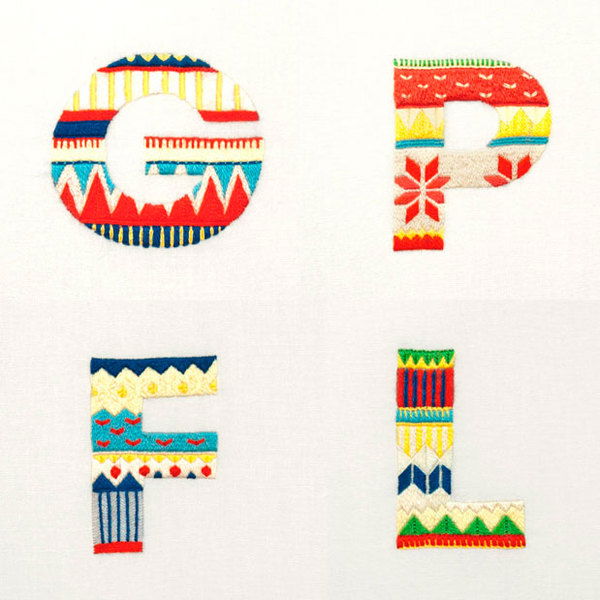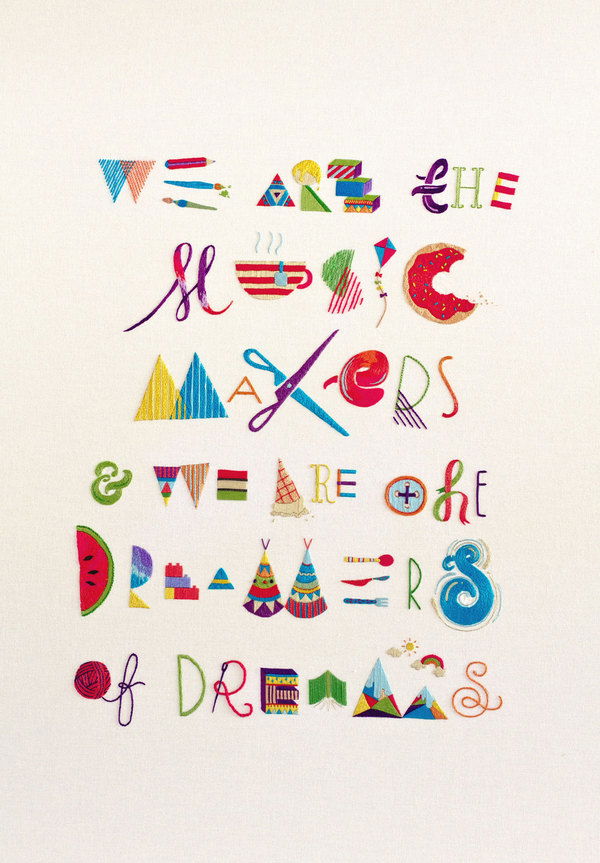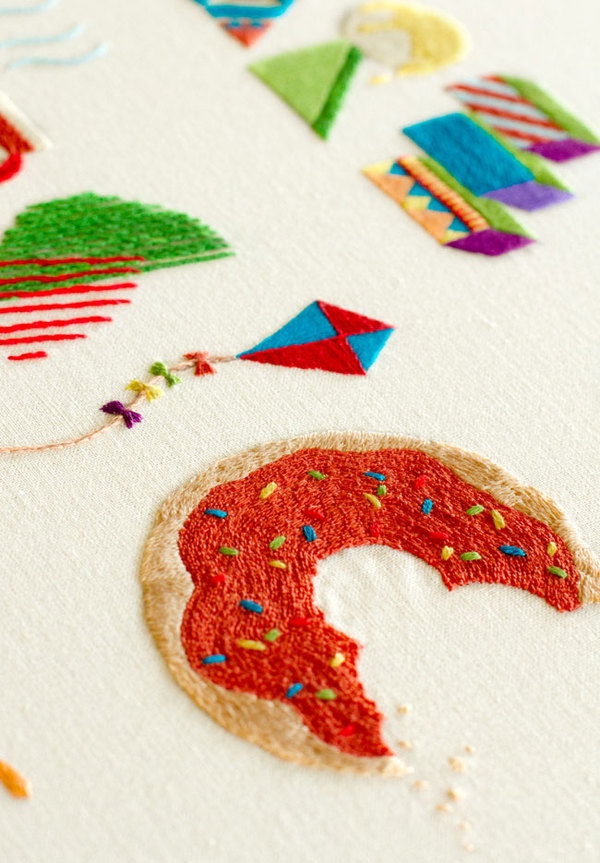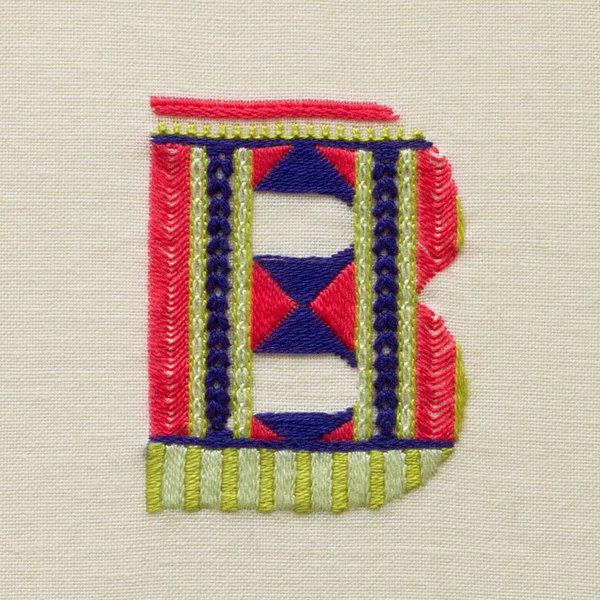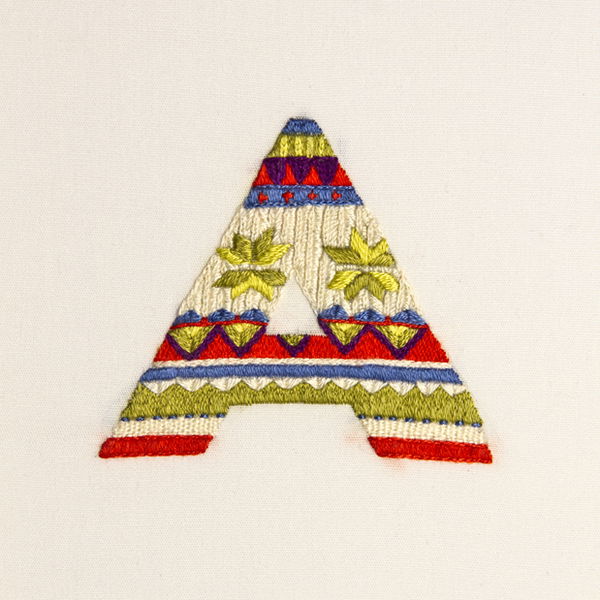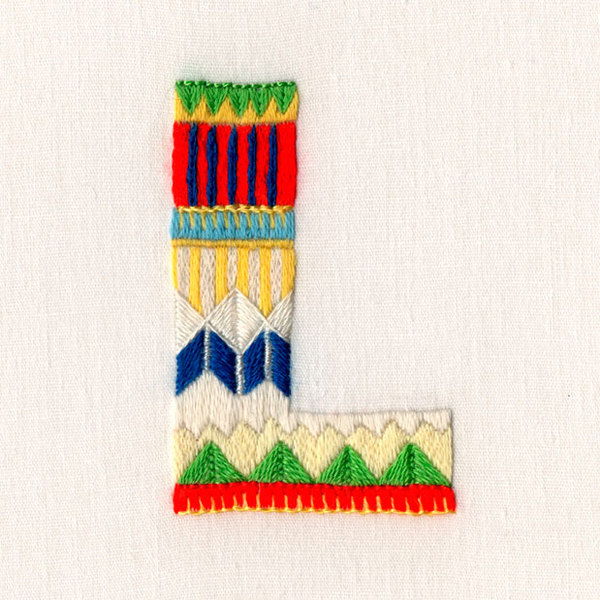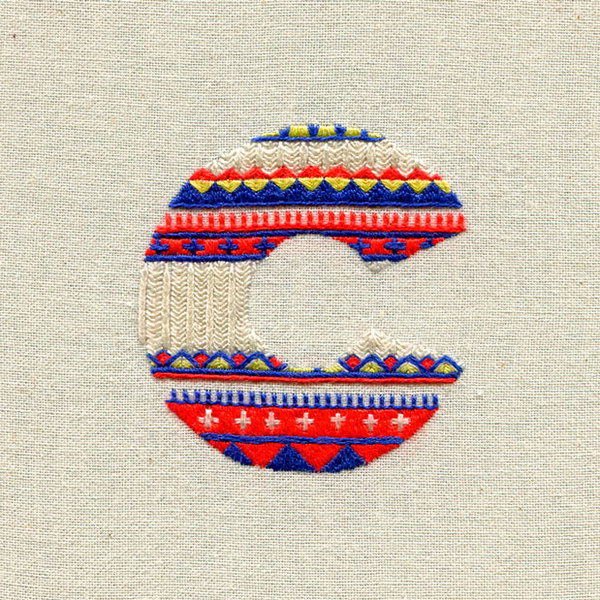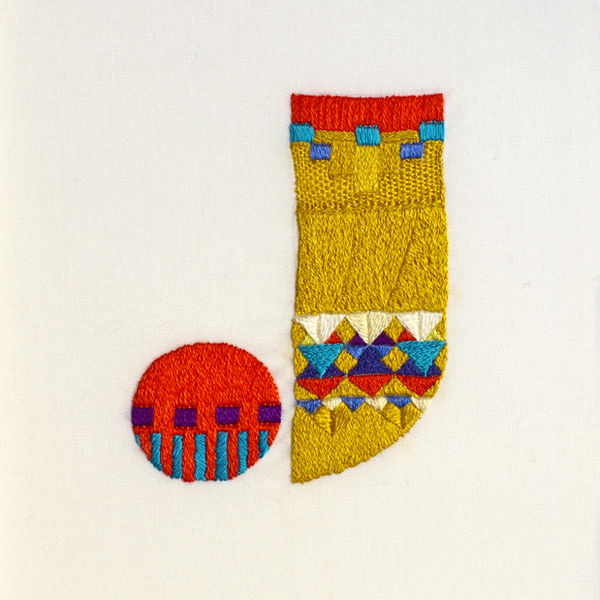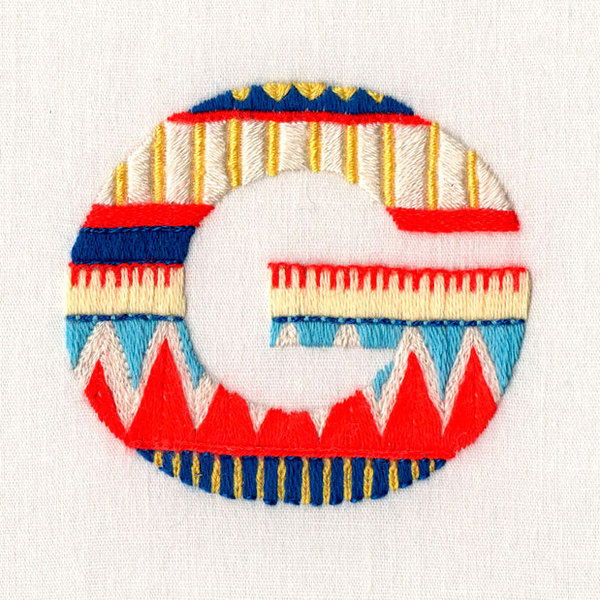
Las tipografías bordadas de MaricorMaricar
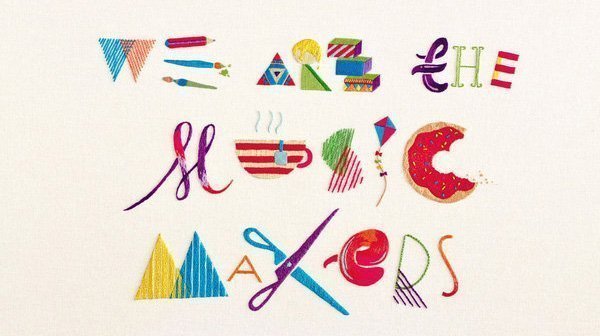
Diseñadoras, ilustradoras, expertas en animación y hermanas gemelas. Las dos australianas forman un estudio llamado MaricorMaricar dedicado a bordar tipografías. ¿Por qué? Porque “es una buena oportunidad de crear algo, con tus manos, fuera del ordenador”, aseguran. “Además, el proceso de trabajo resulta muy meditativo”.
El origen de las letras hechas con hilos está en su “interés por los patrones y el textil”. De ahí surgió la idea de “explorar sobre diseño hecho a mano”, indican las hermanas.
“Empezamos varios años atrás haciendo ilustraciones bordadas. Trabajábamos para un estudio de diseño en Sidney e hicimos un videoclip animado con imágenes hechas en punto”, comentan. “Pero desde entonces hasta la siguiente vez que cogimos una aguja e hilo pasó un tiempo. Volvimos a ello cuando creamos nuestro propio estudio especializado en lettering bordado”.
Maricor y Maricar Manalo han bordado textos para cubiertas de discos, animaciones, vídeos musicales, pósters, revistas y exhibiciones.